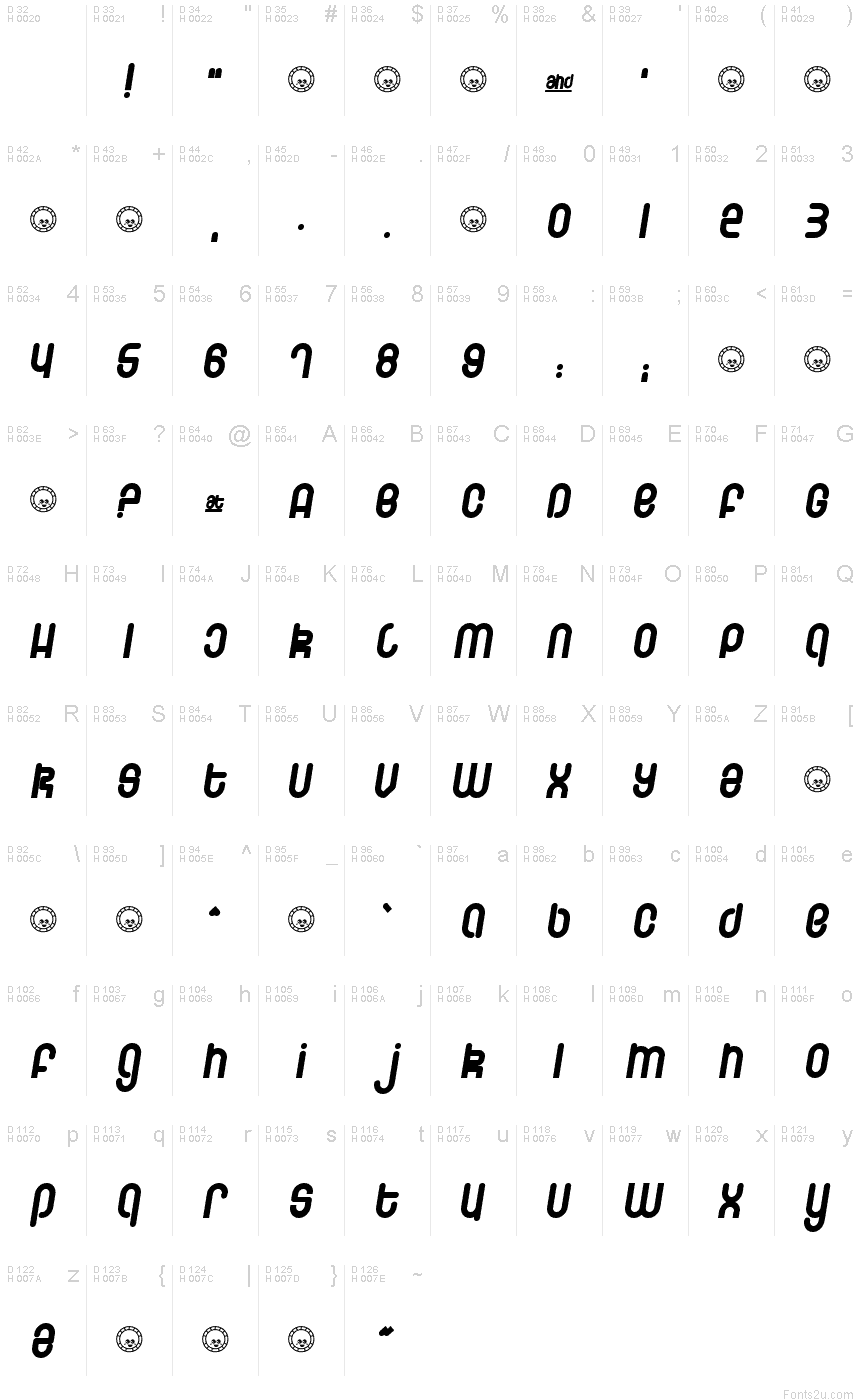
Schmotto Plotto od Schmotto Plotto dla Font"a"licious Fonts to darmowy, nowoczesny krój displayowy o miękkim, "napompowanym" rytmie i zaokrąglonych, niemal płynnych kształtach. Litery mają masywną sylwetkę, ale całość pozostaje raczej zabawna niż ciężka, a wąskie łączenia i obłe zakończenia nadają alfabetowi elastycznego charakteru.
Dzięki temu ten darmowy font naturalnie sprawdza się w identyfikacji wizualnej dla młodych, opakowaniach słodyczy lub przekąsek, okładkach zinów, nagłówkach plakatów i krótkich tytułach, gdzie liczy się płynny, "skoczny" napis. Świetnie sprawdza się również w logotypach i krótkich hasłach, ponieważ powtarzające się zaokrąglone pociągnięcia sprawiają, że nawet kilka liter wydaje się ze sobą połączonych i pełnych ruchu.